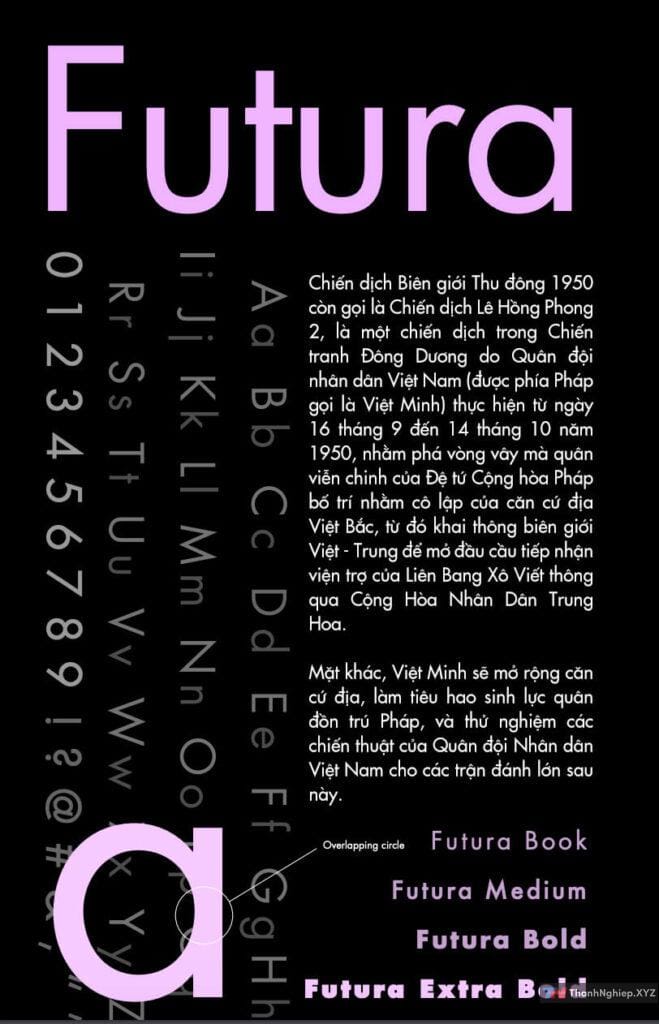
Nếu bạn là dân thiết kế, dân làm content, hay đơn giản là một người yêu cái đẹp của typography, thì bạn chắc chắn không xa lạ gì với Futura – một font chữ huyền thoại gắn liền với sự hiện đại, tinh tế, và tối giản. Nhưng chờ đã, bạn đã biết đến 12 font Futura Việt Hóa chưa? Đây là bộ sưu tập khiến bất cứ ai mê thiết kế cũng phải reo lên: “Wow, đúng cái mình cần!”
Futura là gì mà hot thế?
Ra đời từ những năm 1927 (vâng, đúng rồi, hơn 90 năm trước!), Futura là một font chữ mang phong cách sans-serif hiện đại, lấy cảm hứng từ nghệ thuật hình học Bauhaus. Dù đã tồn tại lâu đời, Futura vẫn luôn nằm trong top các font được yêu thích nhất bởi vẻ đẹp tối giản, sang trọng và linh hoạt. Và khi được Việt Hóa, Futura đã trở thành “vũ khí bí mật” không thể thiếu của các nhà thiết kế Việt Nam.
12 font Futura Việt Hóa – Có gì đặc biệt?
1. Hỗ trợ tiếng Việt hoàn hảo
12 font Futura Việt Hóa được chăm chút tỉ mỉ, đảm bảo mọi dấu câu, ký tự tiếng Việt đều hiển thị đẹp và rõ nét. Bạn không còn lo “đường cong” của dấu hoặc ký tự bị méo mó hay thiếu thẩm mỹ nữa!
2. Đa dạng phong cách
Bộ sưu tập này bao gồm 12 biến thể, từ Futura Light thanh mảnh, tinh tế, đến Futura Bold mạnh mẽ, đầy sức sống. Dù bạn làm thiết kế logo, banner, typography, hay layout sách, báo, font Futura đều có phiên bản phù hợp.
3. Tinh tế nhưng không nhàm chán
Font Futura mang vẻ đẹp tối giản nhưng không hề đơn điệu. Đường nét hình học chuẩn chỉnh, cân đối và thanh thoát giúp thiết kế của bạn luôn nổi bật, dù là trong các dự án cổ điển hay hiện đại.
4. Phù hợp cho mọi nền tảng
5. Ứng dụng rộng rãi
- Logo và nhận diện thương hiệu: Futura tạo cảm giác chuyên nghiệp, hiện đại nhưng không quá lạnh lùng.
- Poster và quảng cáo: Đậm chất “đơn giản là đỉnh cao của phức tạp”, Futura làm mọi thiết kế trở nên sáng sủa và hút mắt.
- Sách, báo và typography: Với khả năng cân đối giữa nội dung chữ và hình ảnh, Futura giúp văn bản dễ đọc mà vẫn đẹp mắt.
Điểm khác biệt của 12 font Futura Việt Hóa
- Việt hóa cực mượt: Không phải font Việt hóa nào cũng đạt độ hoàn hảo, nhưng 12 font Futura Việt Hóa thì khác. Dấu câu, ký tự tiếng Việt đều được tinh chỉnh tỉ mỉ để đồng bộ với bản gốc.
- Tính ứng dụng cực cao: Dù bạn làm dự án cá nhân hay công việc chuyên nghiệp, bộ font này luôn “cân” được mọi phong cách thiết kế.
- Linh hoạt trong mọi dự án: Từ thiết kế in ấn, số hóa, đến quảng cáo hay bài thuyết trình, Futura không bao giờ làm bạn thất vọng.
Vì sao nên sở hữu 12 font Futura Việt Hóa?
- Đẹp, dễ dùng, không lỗi thời: Futura là font chữ vượt thời gian – có thể dùng cho mọi dự án mà không sợ lỗi mốt.
- Tiết kiệm thời gian thiết kế: Không cần tìm kiếm đâu xa, chỉ với 12 biến thể này, bạn đã có đủ lựa chọn để tạo ra mọi kiểu thiết kế.
Bộ font “must-have” cho mọi nhà thiết kế
12 font Futura Việt Hóa không chỉ là một bộ font chữ đơn thuần mà là công cụ giúp bạn nâng tầm sáng tạo và chuyên nghiệp hóa mọi dự án thiết kế. Dù bạn là newbie hay dân chuyên nghiệp, bộ font này chắc chắn sẽ là người bạn đồng hành đáng tin cậy.